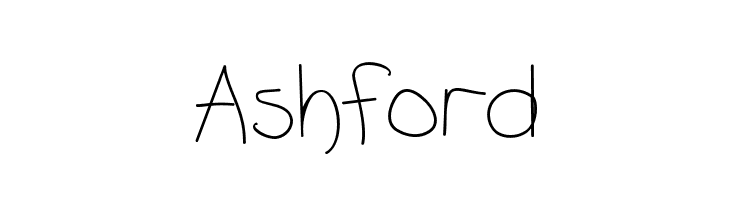
Sacrifice Font
SACRIFICE 大文字
SACRIFICE 小文字
SACRIFICE その他の文字
| 全体的なスタイル | Modern, Artistic |
| おすすめプロジェクト | Ideal for posters, branding, album covers, and any project needing a bold, artistic touch. |